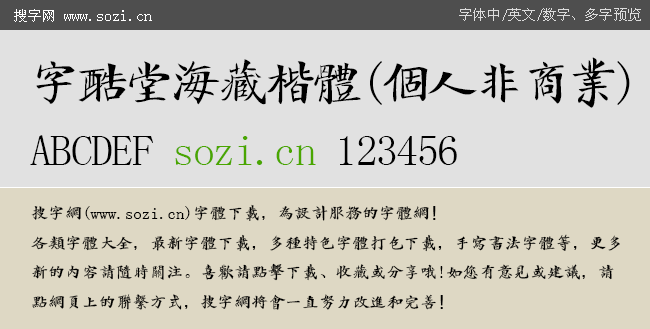
字酷堂海藏楷體(個(gè)人非商業(yè))
搜字網(wǎng)提供一款字酷堂海藏楷體(個(gè)人非商業(yè))中文書(shū)法字體下載,字酷堂海藏楷體是一款非常漂亮的手寫(xiě)風(fēng)格書(shū)法字體,字體端正大方,整體效果非常漂亮,適合應(yīng)用于廣告設(shè)計(jì)、名片設(shè)計(jì)、包裝印刷、海報(bào)設(shè)計(jì)等應(yīng)用。
• 風(fēng)格類別: 手寫(xiě)書(shū)法體